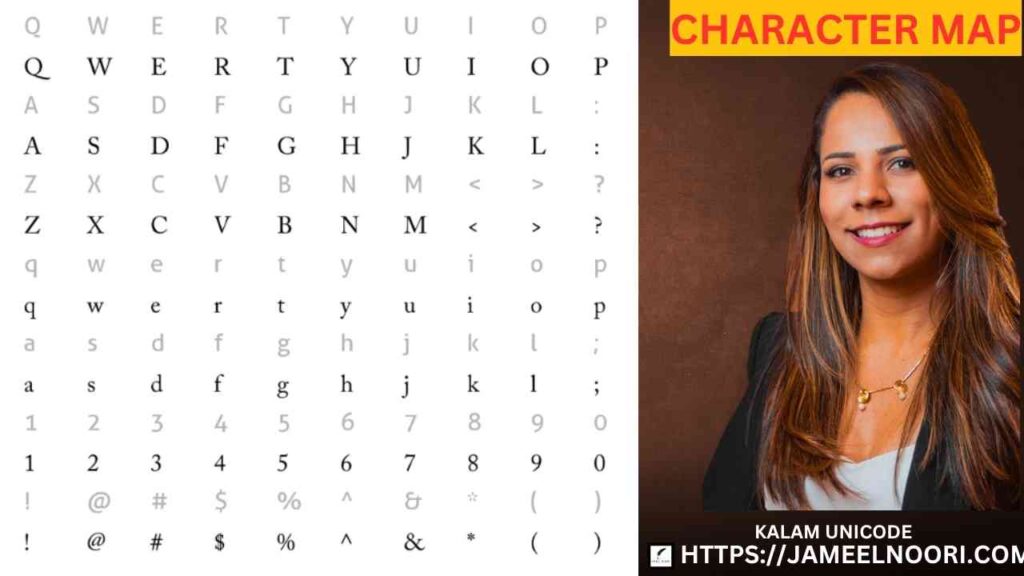
Download Urdu Font Kalam Unicode – Best Free Urdu Font for Pakistan
Agar aap apne computer ya mobile me Urdu typing ke liye stylish aur readable font chahte hain, to Download Urdu Font Kalam Unicode aapke liye best choice hai. Ye ek TrueType Font (TTF) hai jo Windows, Mac, aur Linux systems ke saath compatible hai.
Download Urdu Font Kalam Unicode Features
Download Urdu Font Kalam Unicode ke kuch main features ye hain:
- ✅ High readability for both print and digital
- ✅ Stylish yet professional Urdu typography
Why Choose Kalam Unicode for Urdu Typing
Download Urdu Font Kalam Unicode ko choose karne ke kuch solid reasons hain:
- Easy readability – Long Urdu paragraphs me bhi clear text.
- Professional look – Official documents aur certificates ke liye perfect.
Conclusion – Download Urdu Font Kalam Unicode Today
Agar aap Urdu writing ko stylish aur readable banana chahte hain, to Download Urdu Font Kalam Unicode aapke liye best option hai. Iska clean design, compatibility aur free availability isay Pakistan ke graphic designers, students, aur bloggers ka favourite banata hai.
Is Kalam Unicode suitable for logo design?
Yes, its stylish yet professional look makes it perfect for logo designing.
Does Kalam Unicode support all Urdu characters?
Yes, it includes all standard Urdu alphabets, numerals, and diacritics.